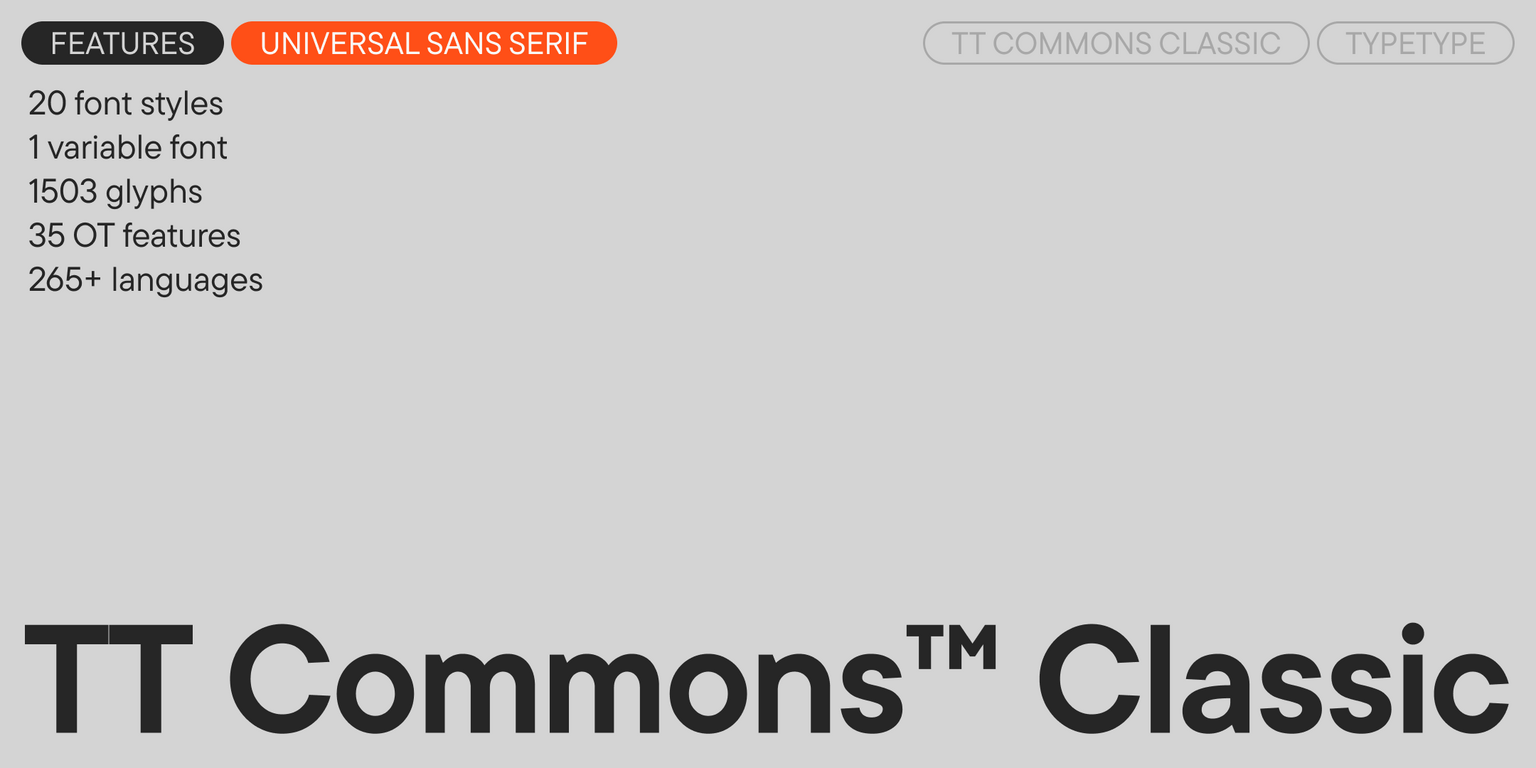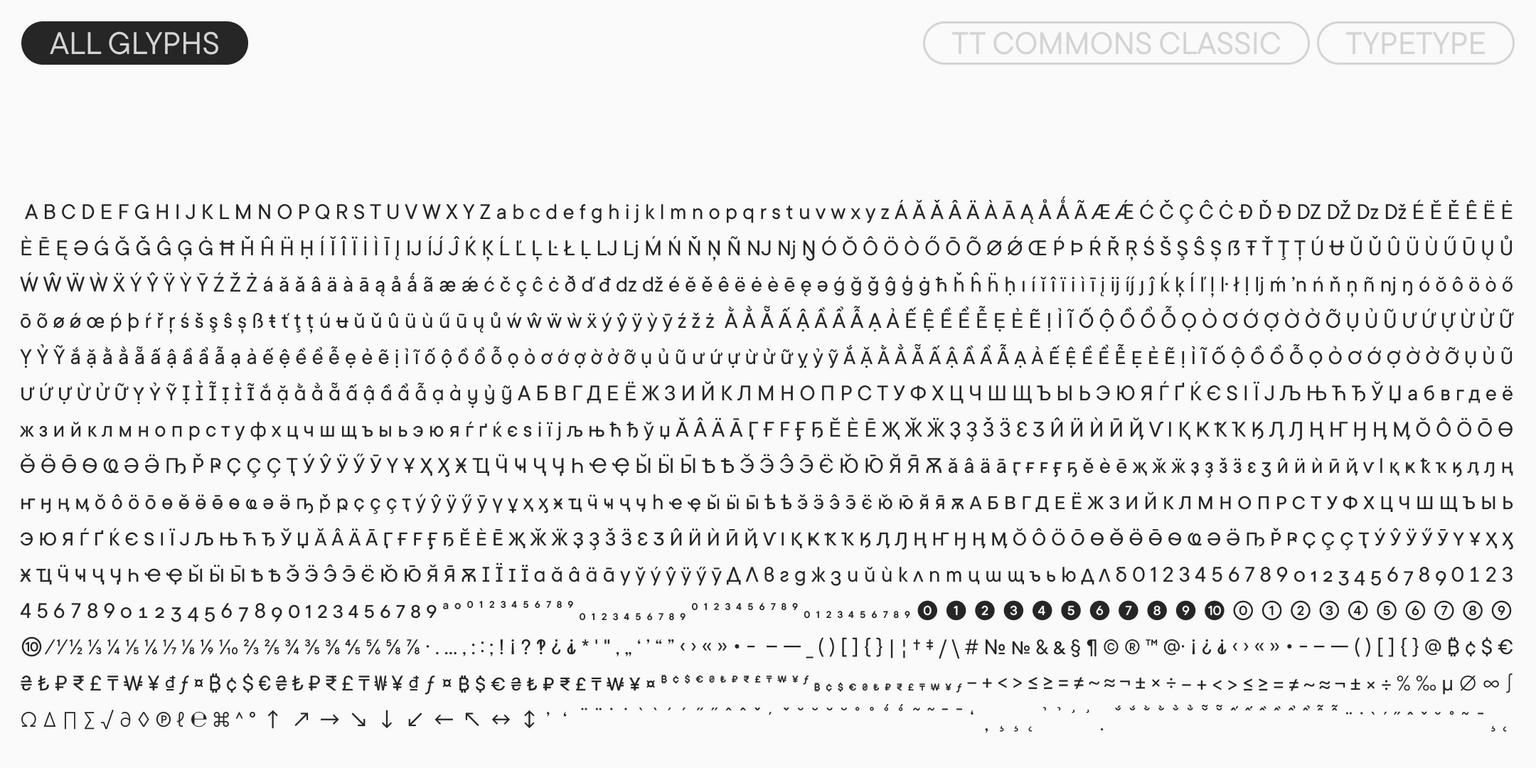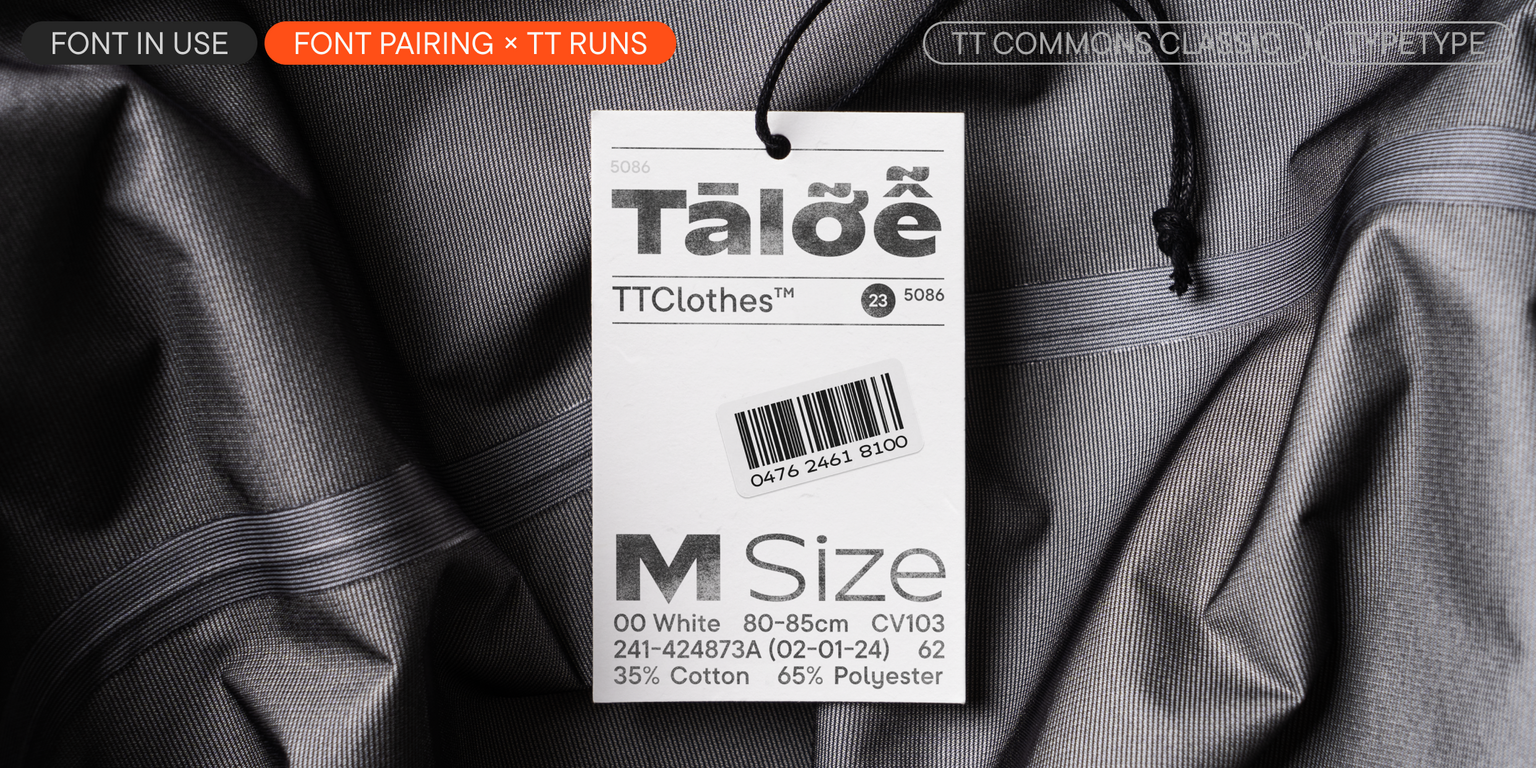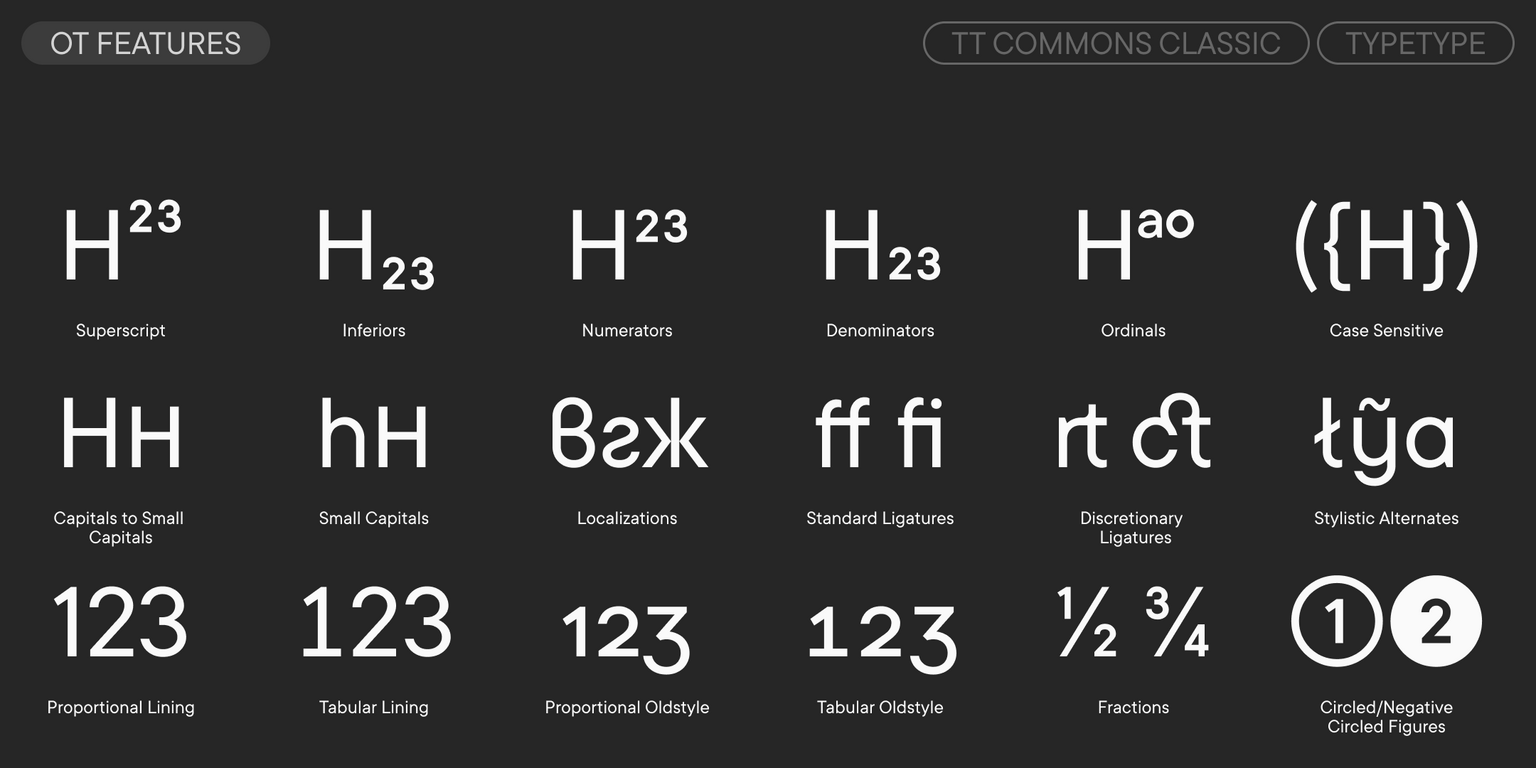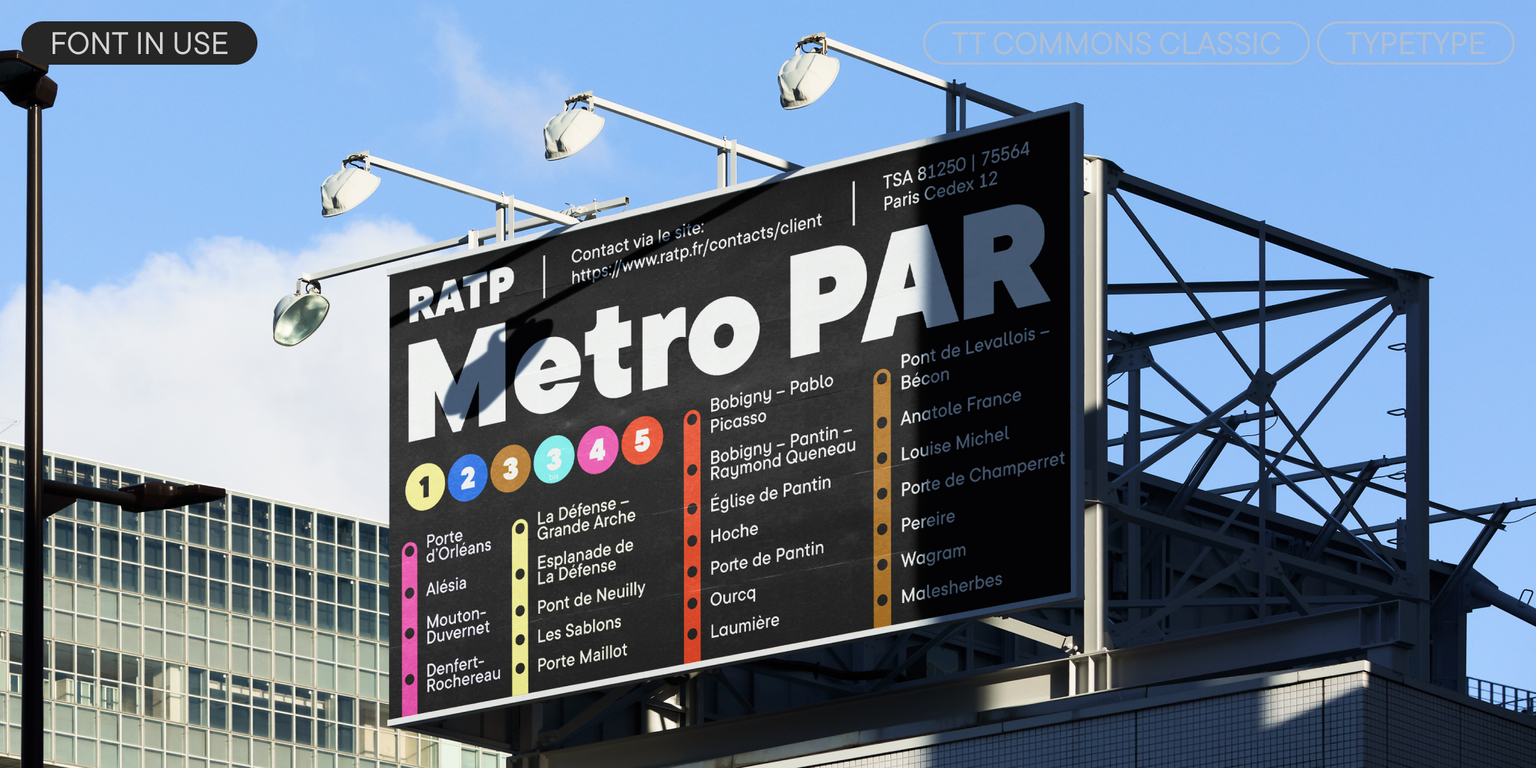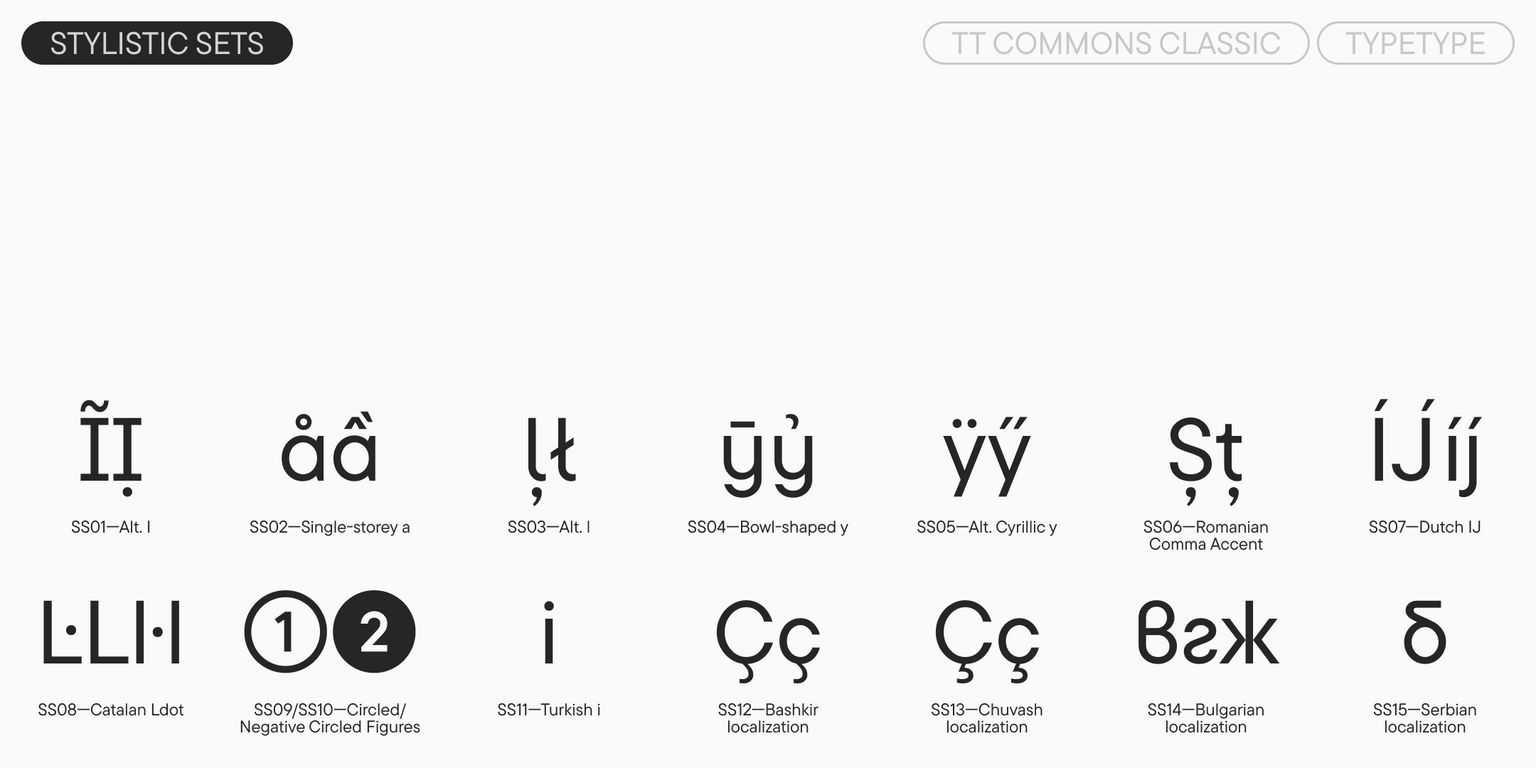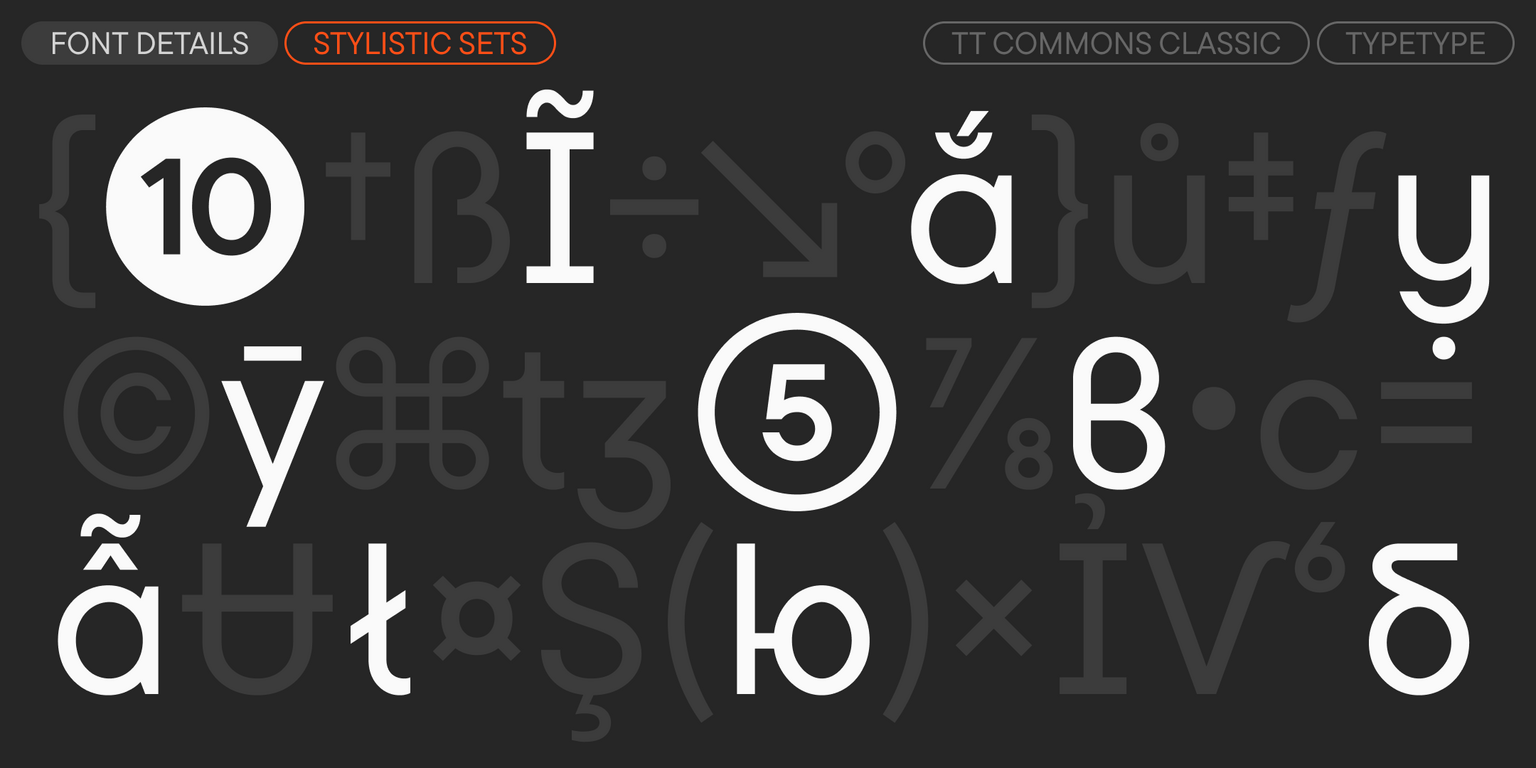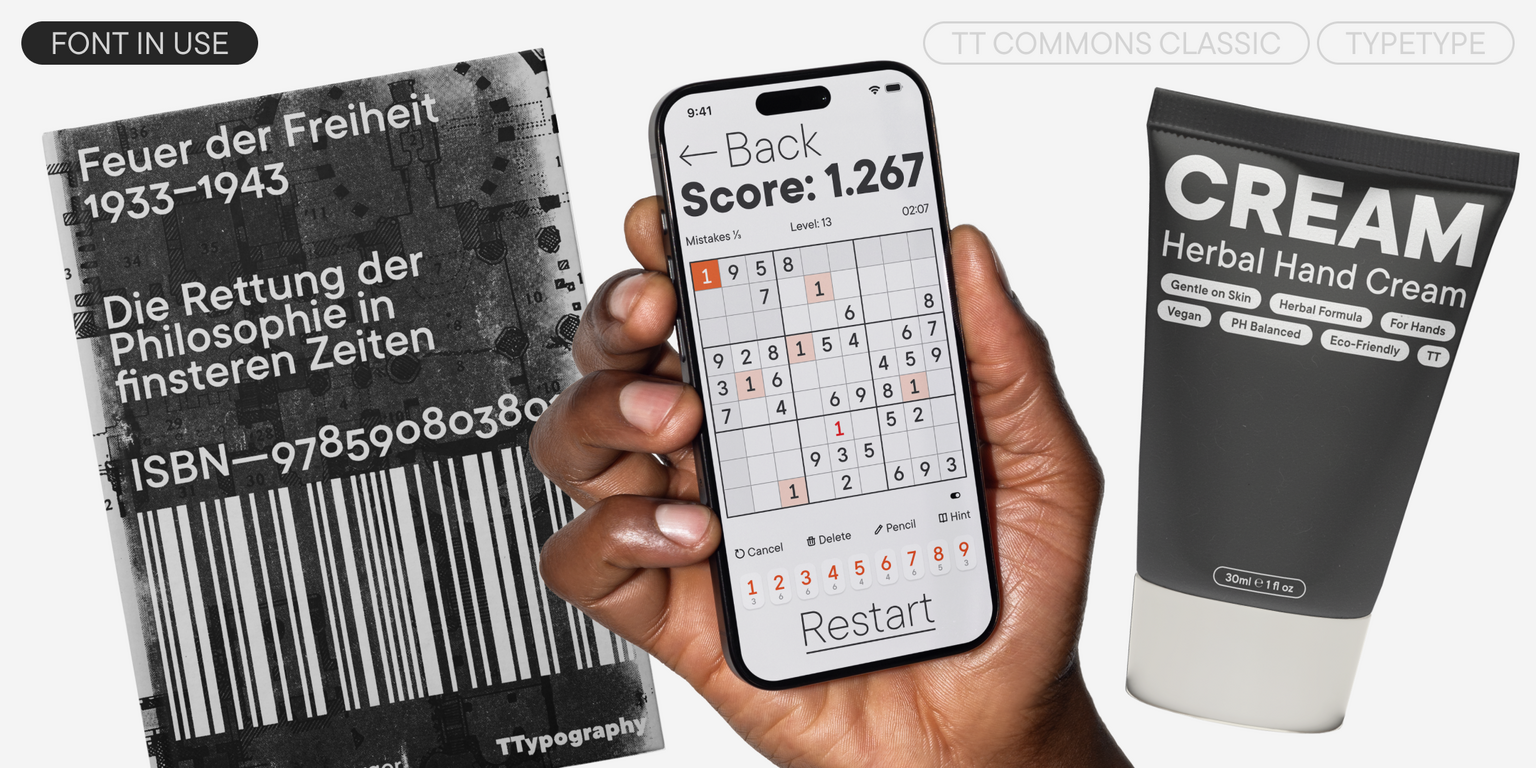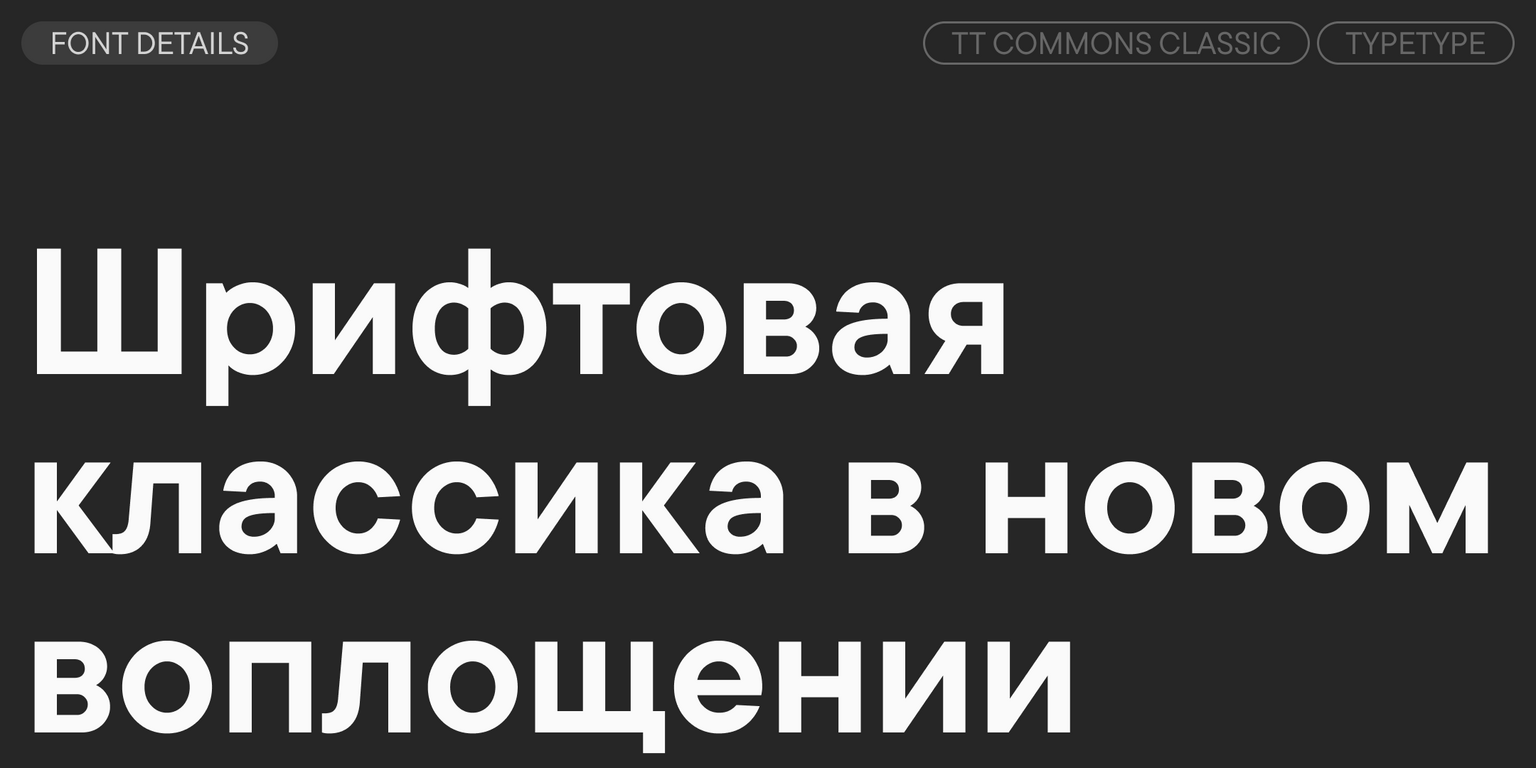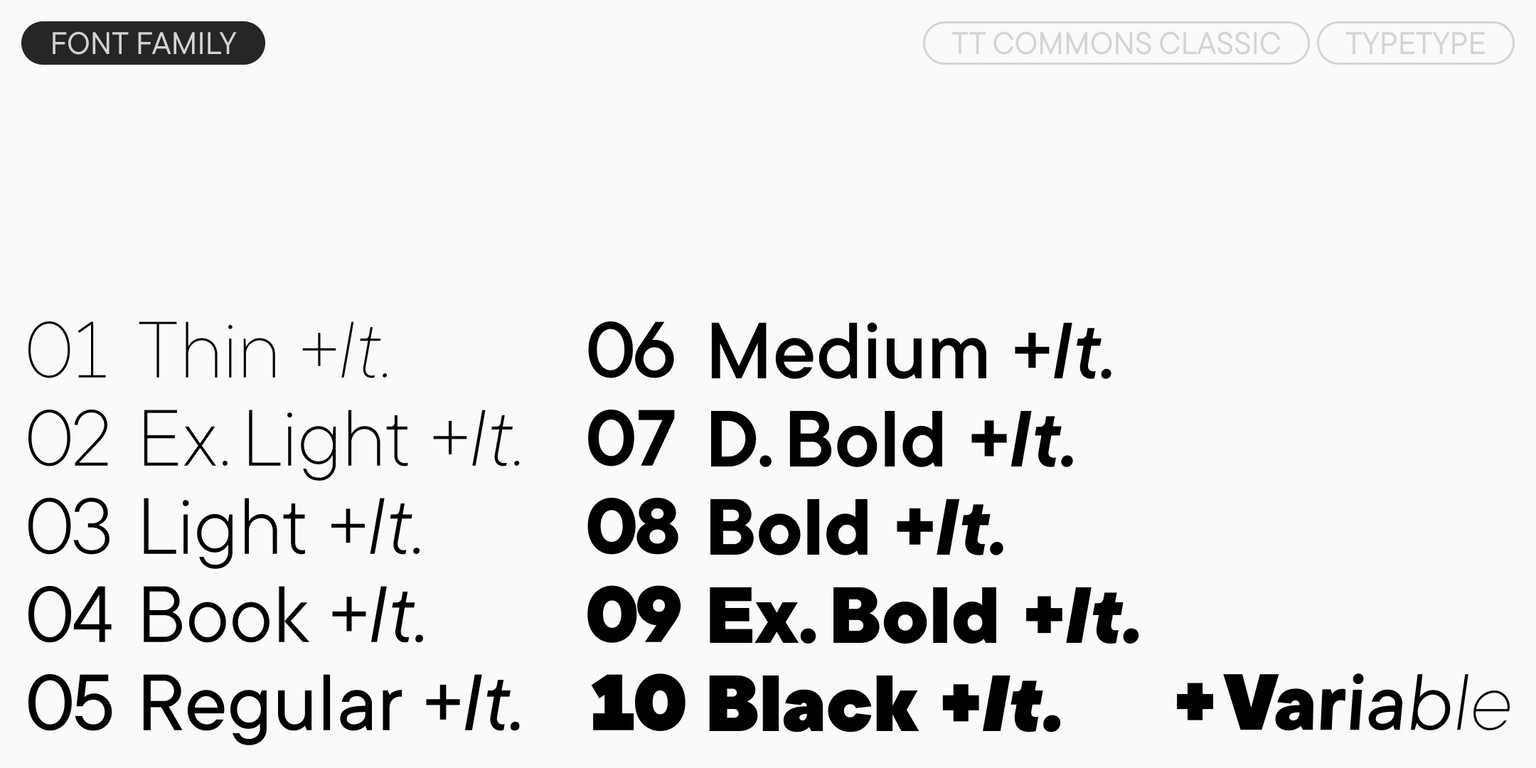
TT Commons™ Classic
TT Commons™ Classic — TT Коммонс Классик
«TT Commons» является зарегистрированным товарным знаком. «Classic» произносится как «классик», в переводе с английского «классический».
TT Commons™ Classic — универсальный геометрический гротеск для широкого круга задач.
TT Commons™ Classic — универсальный гротеск
Дизайн гарнитуры разрабатывался для максимально широкого круга задач, с которыми обязан справляться любой качественный корпоративный шрифт. Низкий контраст штрихов и усредненный рисунок букв делает TT Commons™ Classic превосходным для набора больших массивов текста. С другой стороны, индивидуальная проработка дизайна позволяет использовать его и для акциденции.
Название TT Commons™ Classic идет от слова ’common’ (общепринятый, типичный, частый)
Этот шрифт можно использовать для любых повседневных задач
TT Commons™ Classic в дизайне
О гарнитуре TT Commons™ Classic
Встречайте TT Commons™ Classic версии 2.200!
Обновили начертания, добавили новые фичи, знаки и языки.
TT Commons™ Classic — универсальный гротеск для повседневных задач. Его история неразрывно связана с историей TypeType: изначально он был официальным корпоративным шрифтом студии, созданным исключительно для внутреннего использования. Однако благодаря активному интересу пользователей вскоре превратился в полноценную коммерческую гарнитуру.
Название происходит от слова «common» (общепринятый, типичный, частый). Дизайн шрифта разработан так, чтобы его можно было использовать для максимально широкого круга задач. Минимальный контраст штрихов, закрытая апертура и геометрические формы делают TT Commons™ Classic идеальным для набора больших массивов текста. С другой стороны, его можно использовать и для акциденции, несмотря на намеренное отсутствие декоративных элементов: шрифт притягивает внимание своей лаконичностью, простотой и отточенностью форм.
В обновлённую версию мы добавили усовершенствованный вариативный шрифт, объединив два начертания (для прямых и наклонных знаков) в единую вариативную систему. Кроме того, появились новые OpenType фичи, языки и знаки, в том числе знаки для расширенной латиницы.
Благодаря своей минималистичности и нейтральному характеру TT Commons™ Classic подходит для любых сфер. А капители, стилистические альтернативы, лигатуры, стрелки, разные типы цифр и другие фичи делают гарнитуру ещё более функциональной. TT Commons™ Classic и бестселлер TT Commons™ Pro базируются на одной графике, однако у них разное наполнение и возможности использования. TT Commons™ Classic подойдёт вам, если вы ищите проверенные решения для регулярных задач, а TT Commons™ Pro — если необходим расширенный функционал с большим количеством начертаний, фич, стилистических сетов и языков.
В TT Commons™ Classic 2.200 входит:
• 21 начертание: 10 прямых, 10 наклонных и 1 вариативное;
• 1503 знака в каждом начертании;
• 35 OpenType фич;
• 265+ языков.
TT Commons™ Classic — безупречная шрифтовая классика!
Что изменилось в шрифте:
• Количество начертаний изменилось с 24 до 21: мы добавили усовершенствованный вариативный шрифт, объединив два начертания (для прямых и наклонных знаков) в единую вариативную систему, а также удалили начертания Outline и Outline Italic;
• Количество знаков в каждом начертании выросло с 1437 до 1503, в частности, мы дорисовали знаки для расширенной латиницы;
• Количество OpenType фич выросло с 29 до 35;
• Количество языков выросло с 260+ до 265+: появились German+, Uzbek (lat), Marshallese, Bulgarian (lat), Guarani, Macedonian+, Nenets+.
liga | Standard Ligatures
fl ffi
dlig | Discretionary Ligatures
fk ffh
smcp | Small Caps
abcd
onum | Oldstyle Figures
1638
case | Case Sensitive Forms
({[H]})
ss01 | Alternative I